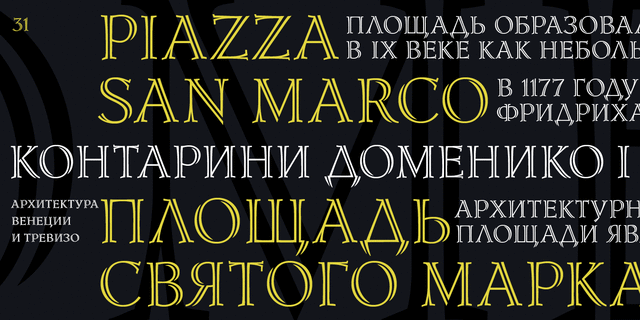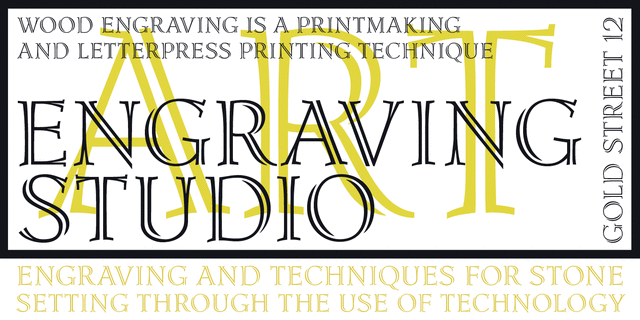
Декоративный титульный шрифт был разработан в Отделе наборных шрифтов НИИ Полиграфмаш в 1967 году дизайнером Ираидой Чепиль. Рисунок представляет собой декоративный вариант ('с просветом') классической антиквы. Предназначен для набора заголовков в журналах, листовой продукции и другой акциденции. Переработанная и дополненная цифровая версия разработана для фирмы ПараТайп в 2005 году дизайнером Виктором Хариком.